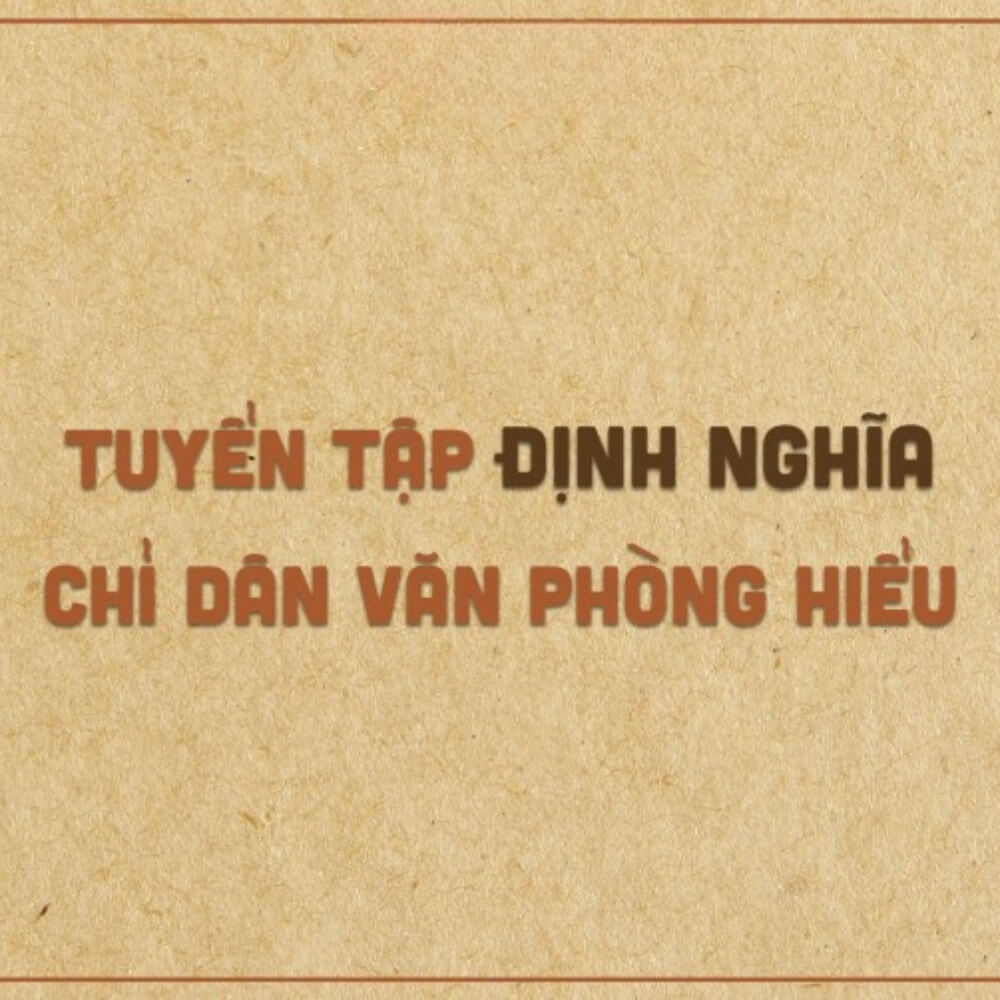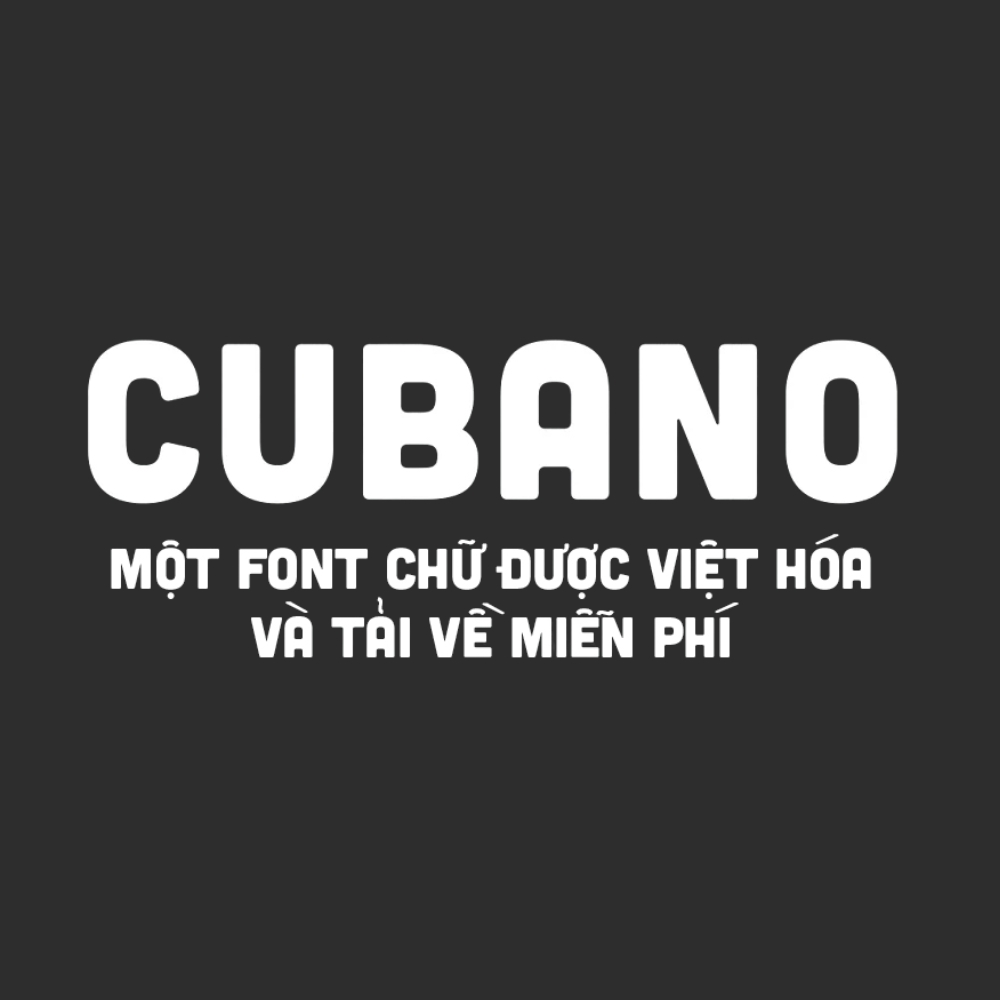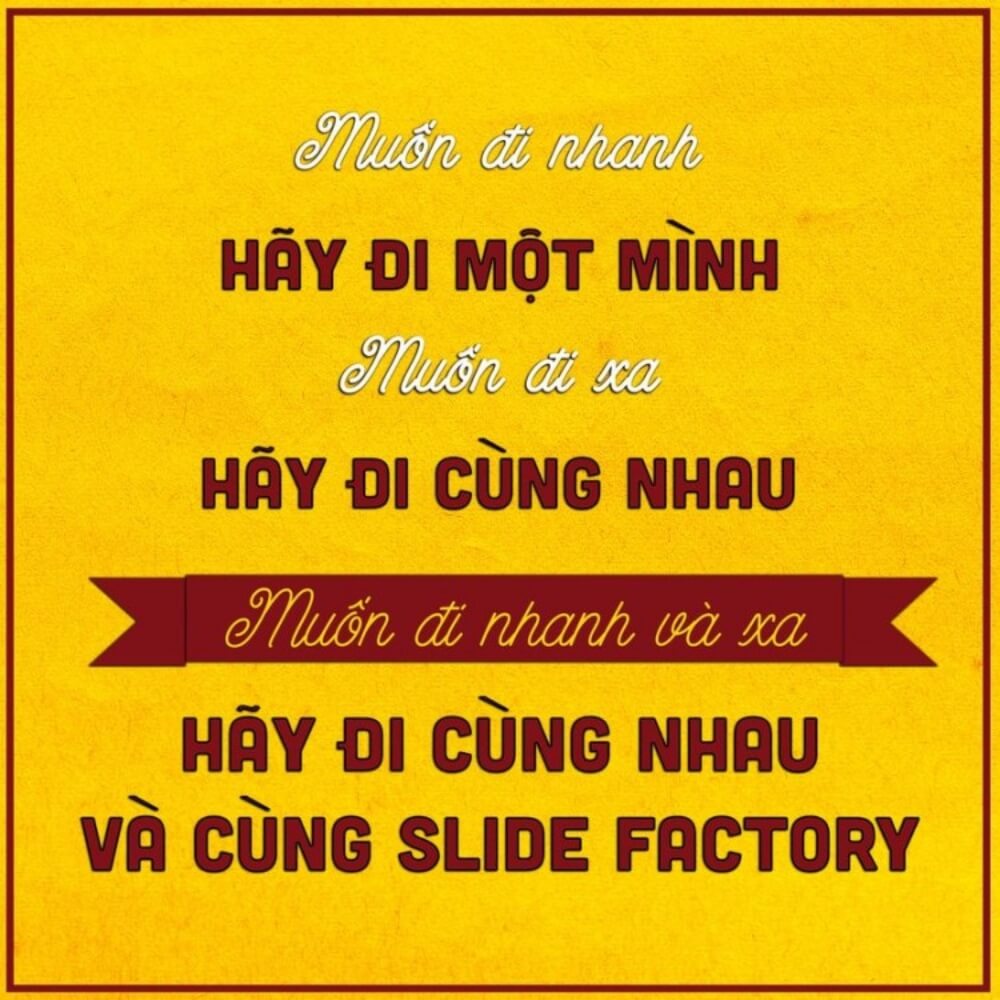
| Kiểu chữ | Display Sans |
| Ứng dụng | Poster, logo, banner, tiêu đề |
Bộ font icielbc việt hóa này thường được designer sử dụng khi cần tạo tiêu đề nổi bật trong các ấn phẩm quảng cáo hoặc thiết kế nhận diện thương hiệu.
Đặc điểm nổi bật của font Việt hóa iCiel BC Cubano Normal
Trong các font display hiện đại, font Việt hóa iCiel BC Cubano Normal được đánh giá cao nhờ cấu trúc chữ mạnh mẽ và dễ nhận diện. Font này thường xuất hiện trong các thiết kế quảng cáo hoặc branding.
Những điểm nổi bật của font iciel cubano việt hóa có thể kể đến:
- Nét chữ dày, chắc và rõ ràng.
- Phong cách chữ hiện đại và mạnh mẽ.
- Dễ đọc ở kích thước lớn.
- Tạo điểm nhấn tốt cho tiêu đề hoặc logo.
Nhờ những đặc điểm này, Font Cubano thường được sử dụng trong thiết kế poster, banner hoặc các chiến dịch marketing cần gây ấn tượng thị giác mạnh.
Ứng dụng font Cubano trong thiết kế poster và logo
Nhờ hình khối chữ rõ ràng, phông chữ Việt hóa iCiel BC Cubano Normal có thể ứng dụng linh hoạt trong nhiều loại thiết kế khác nhau. Designer thường lựa chọn font này khi cần một kiểu chữ nổi bật và dễ nhận diện.
- Poster sự kiện.
- Banner quảng cáo.
- Thiết kế logo thương hiệu.
- Bao bì sản phẩm
Khi sử dụng đúng cách, font việt hóa iCiel BC Cubano Normal có thể giúp thiết kế trở nên mạnh mẽ và thu hút hơn.
03 lưu ý khi sử dụng font Cubano trong thiết kế
Mặc dù font việt hóa iCiel BC Cubano Normal rất phù hợp cho tiêu đề và logo, nhưng nếu sử dụng không đúng cách có thể làm bố cục thiết kế bị nặng hoặc khó đọc.
- Không nên dùng cho đoạn văn dài: font display thường phù hợp với tiêu đề hơn là nội dung văn bản.
- Nên dùng cho logo hoặc headline: nét chữ dày giúp tạo điểm nhấn mạnh cho thiết kế.
Những lưu ý này sẽ giúp designer tận dụng tốt hơn font icielbc việt hóa trong các dự án thiết kế thực tế.
Ứng dụng font việt hóa iCiel BC Cubano Normal trong in ấn
Trong ngành in ấn, những font chữ có nét rõ và dày như font việt hóa iCiel BC Cubano Normal thường cho kết quả hiển thị rất tốt trên nhiều chất liệu khác nhau.